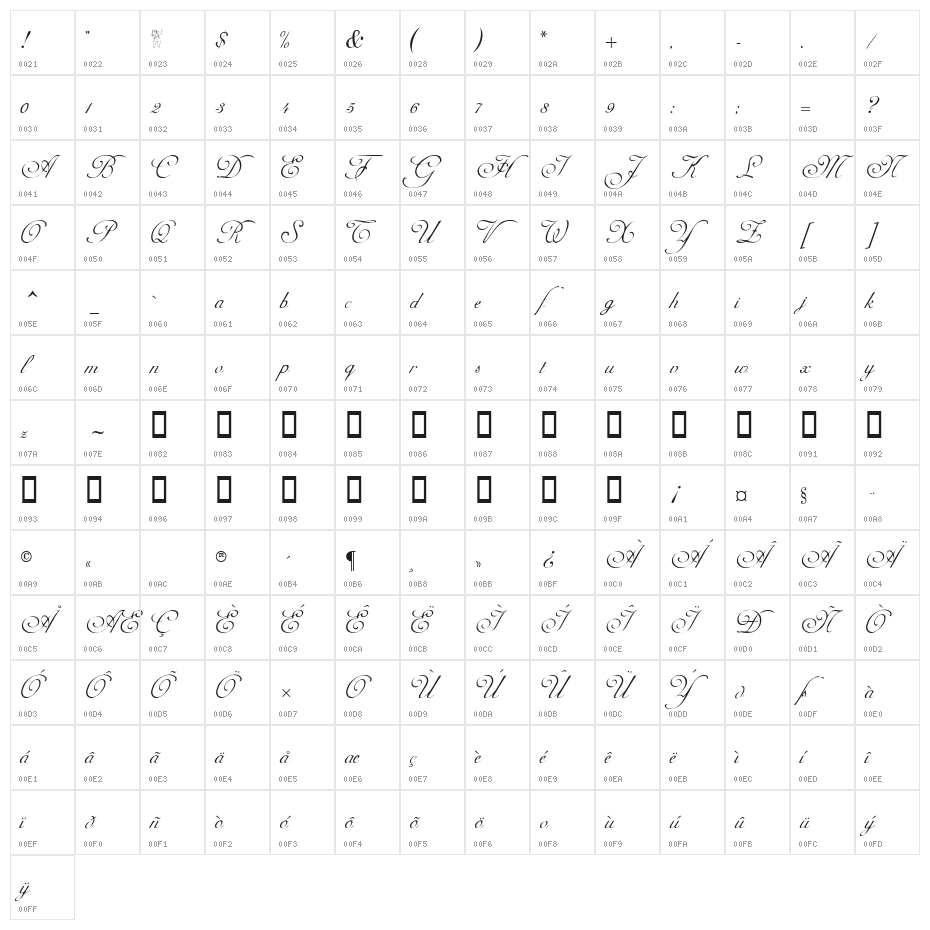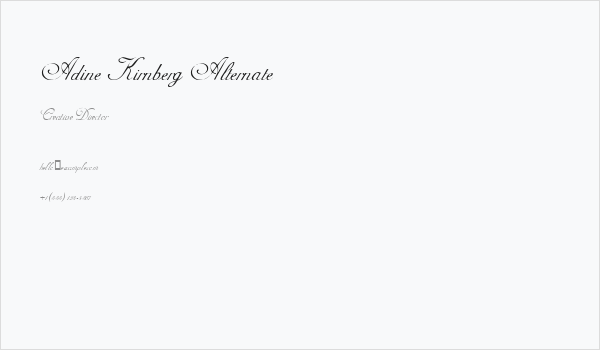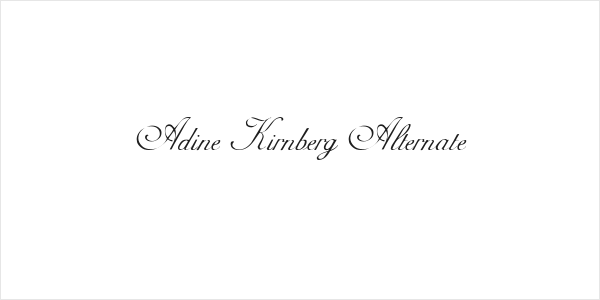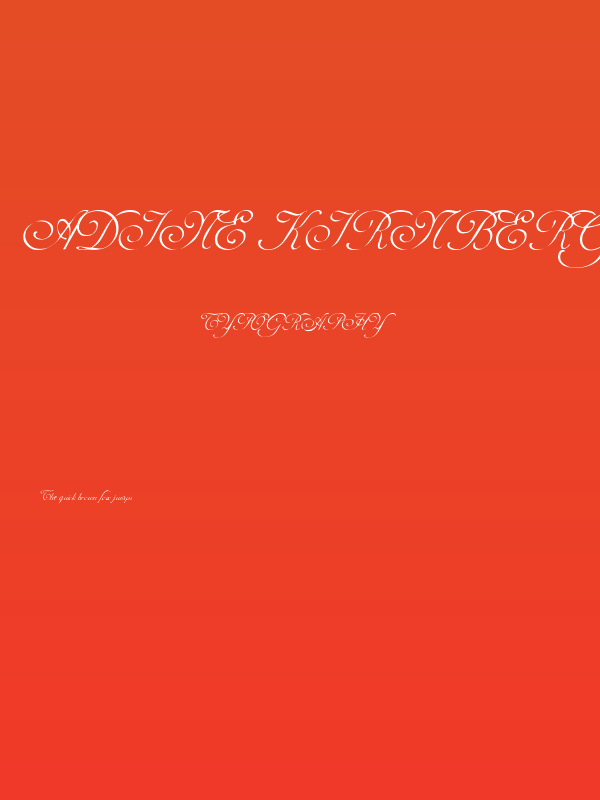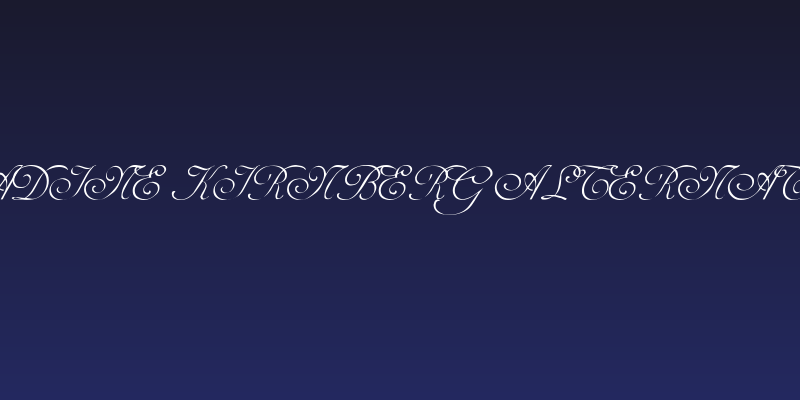
Adine Kirnberg Alternate Font
✎ Art Nouveau
Fonts by Dieter Steffmann
| Categorías | Art Nouveau |
| Estilo general | Classic |
| Proyectos propuestos | Ideal for wedding invitations, formal event programs, luxury branding, and decorative certificates. |